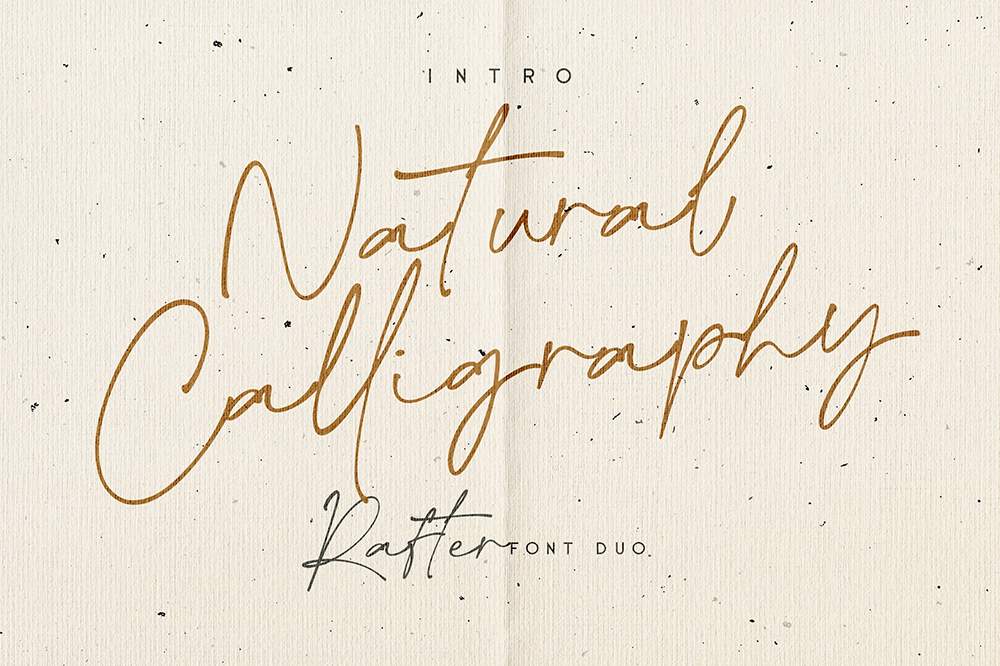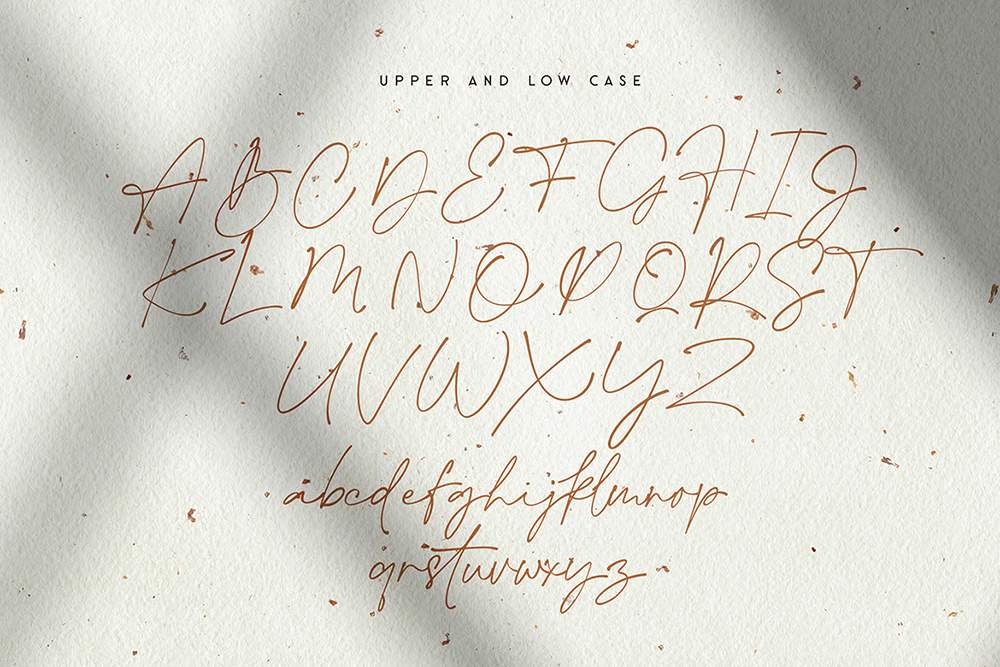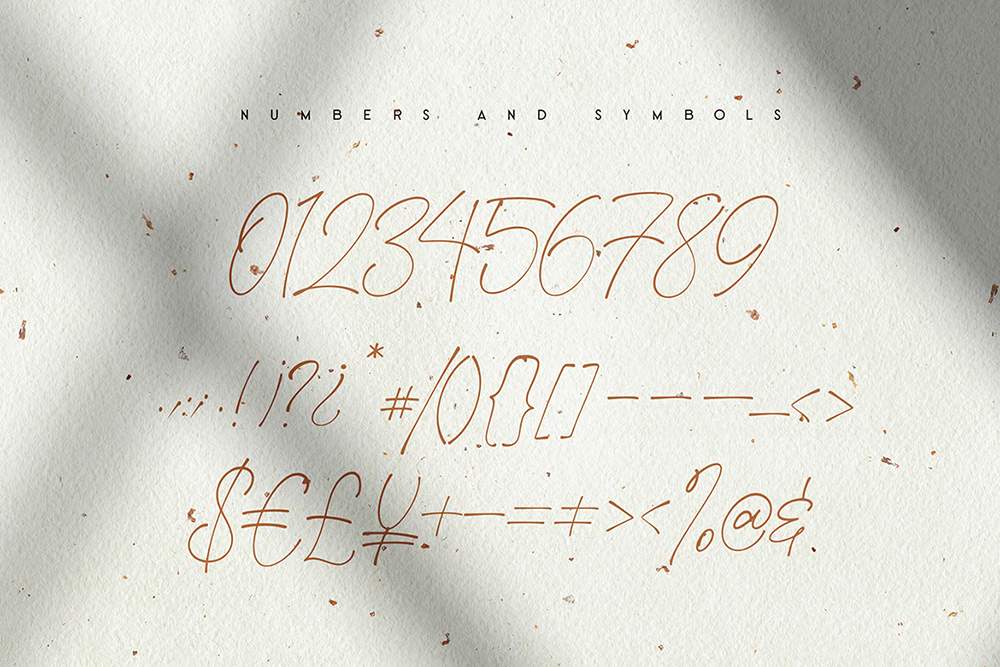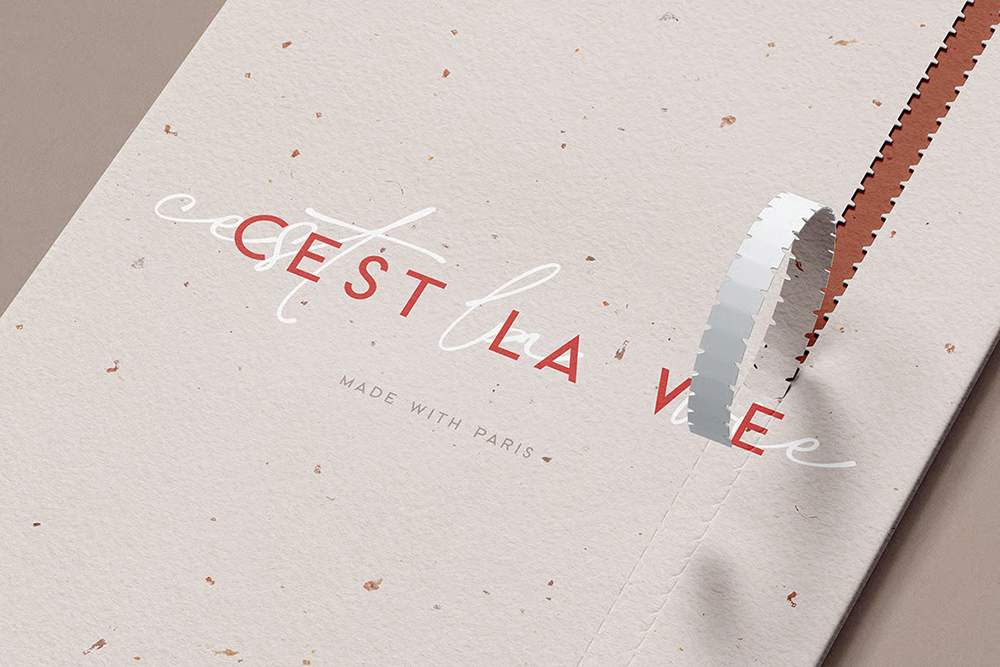
فونت پرمیوم و انگلیسی Rafter Font يک فونت مدرن و نمايشی پر از ليگاتورهای عجيب و غريب و گليفها است. برای مجلات (عنوانها و طرحبندیها)، لوگوها و برندسازی، دعوتنامهها، نقل قولها، سربرگهای وبلاگ، پوسترها و تبليغات و موارد دیگر عالی است.